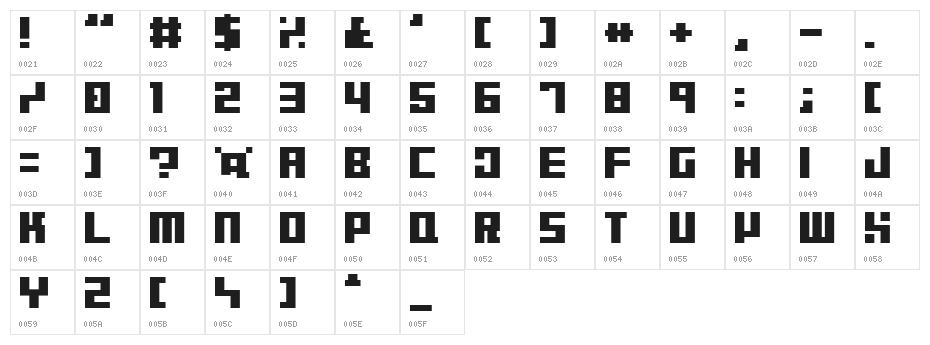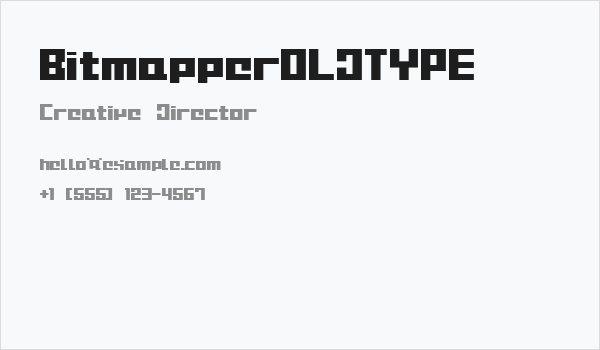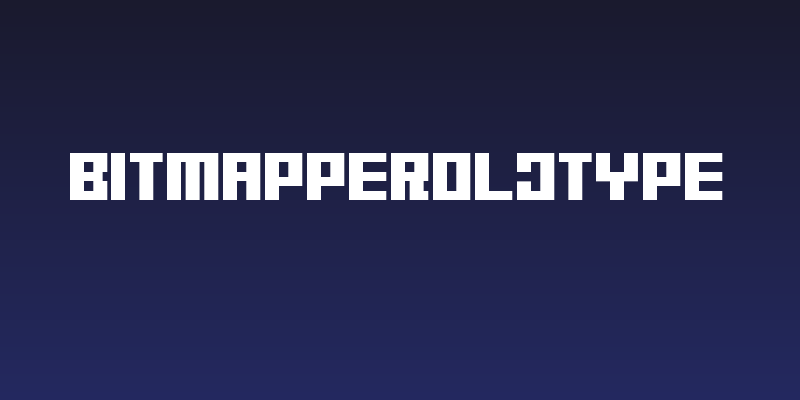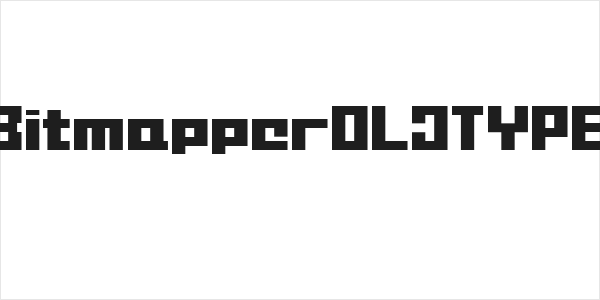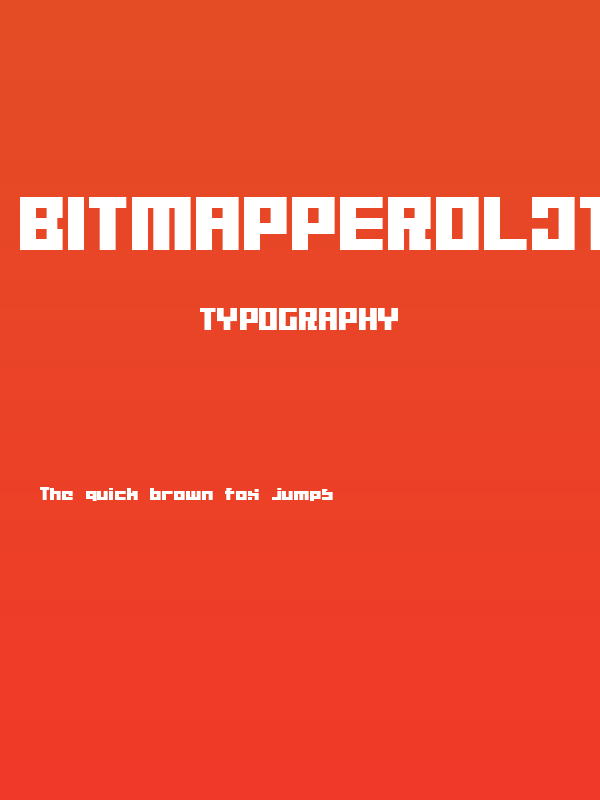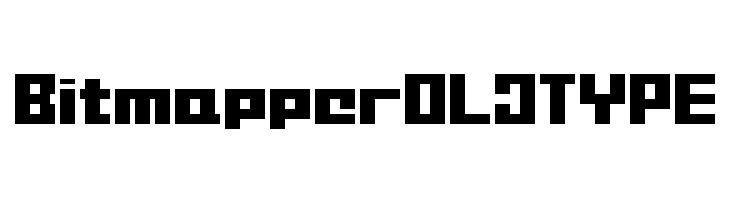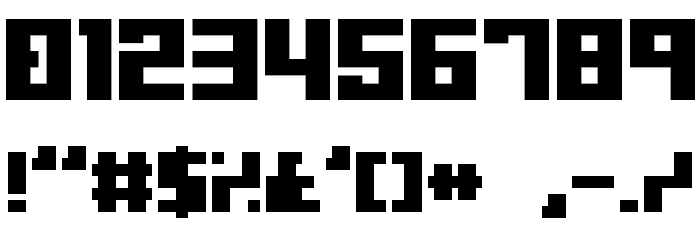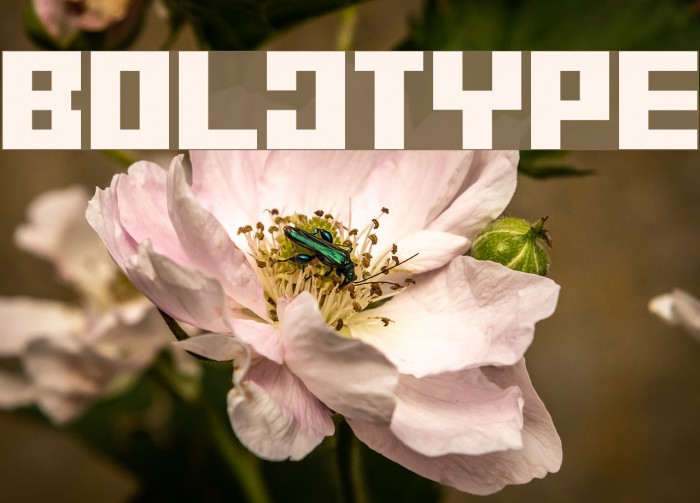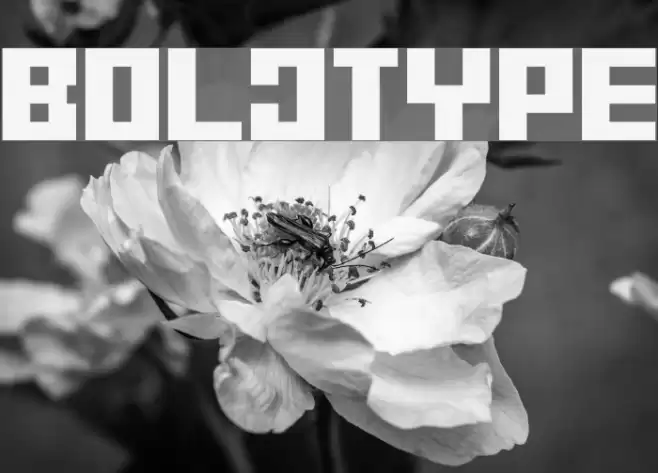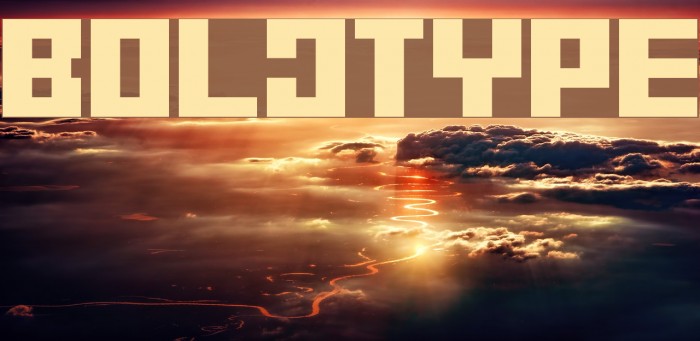
BitmapperOLDTYPE Font
| श्रेणियाँ | Pixel |
| समग्र शैली | Vintage |
| उपयोग का मामला | Logos, Headlines, Posters |
| सुझाए गए प्रोजेक्ट | Ideal for video game designs, retro-themed posters, digital art projects, and any creative work that seeks a nostalgic or tech-inspired look. |